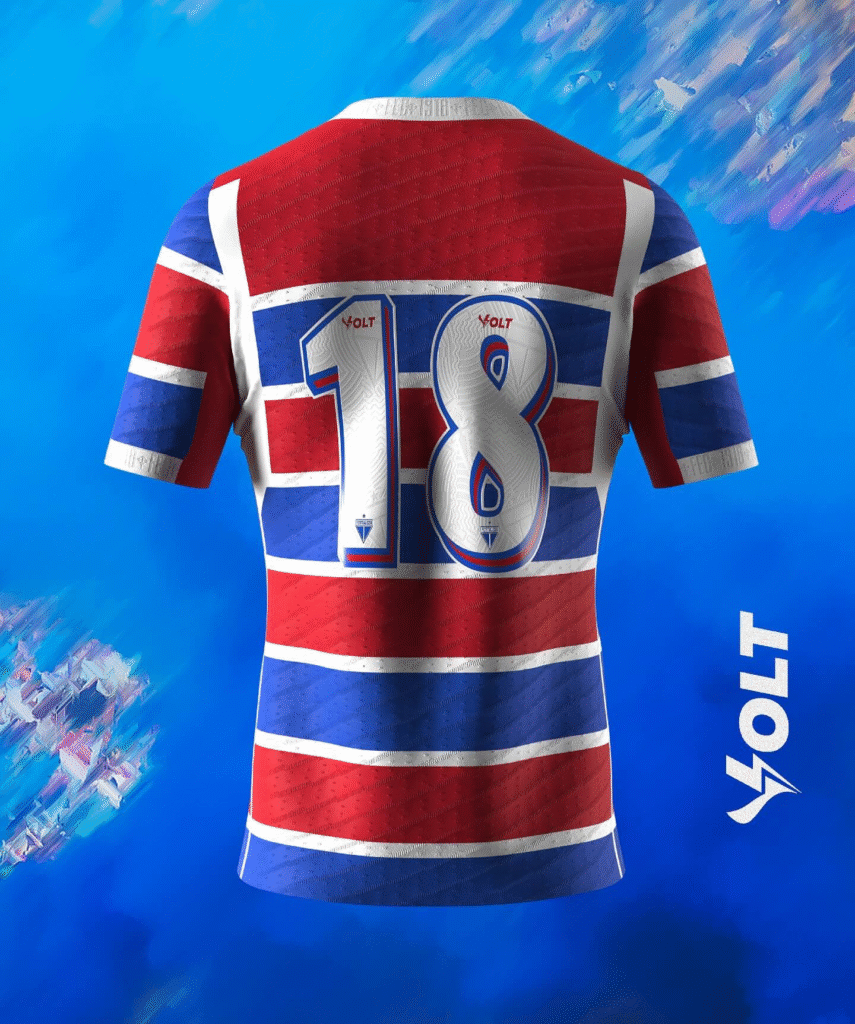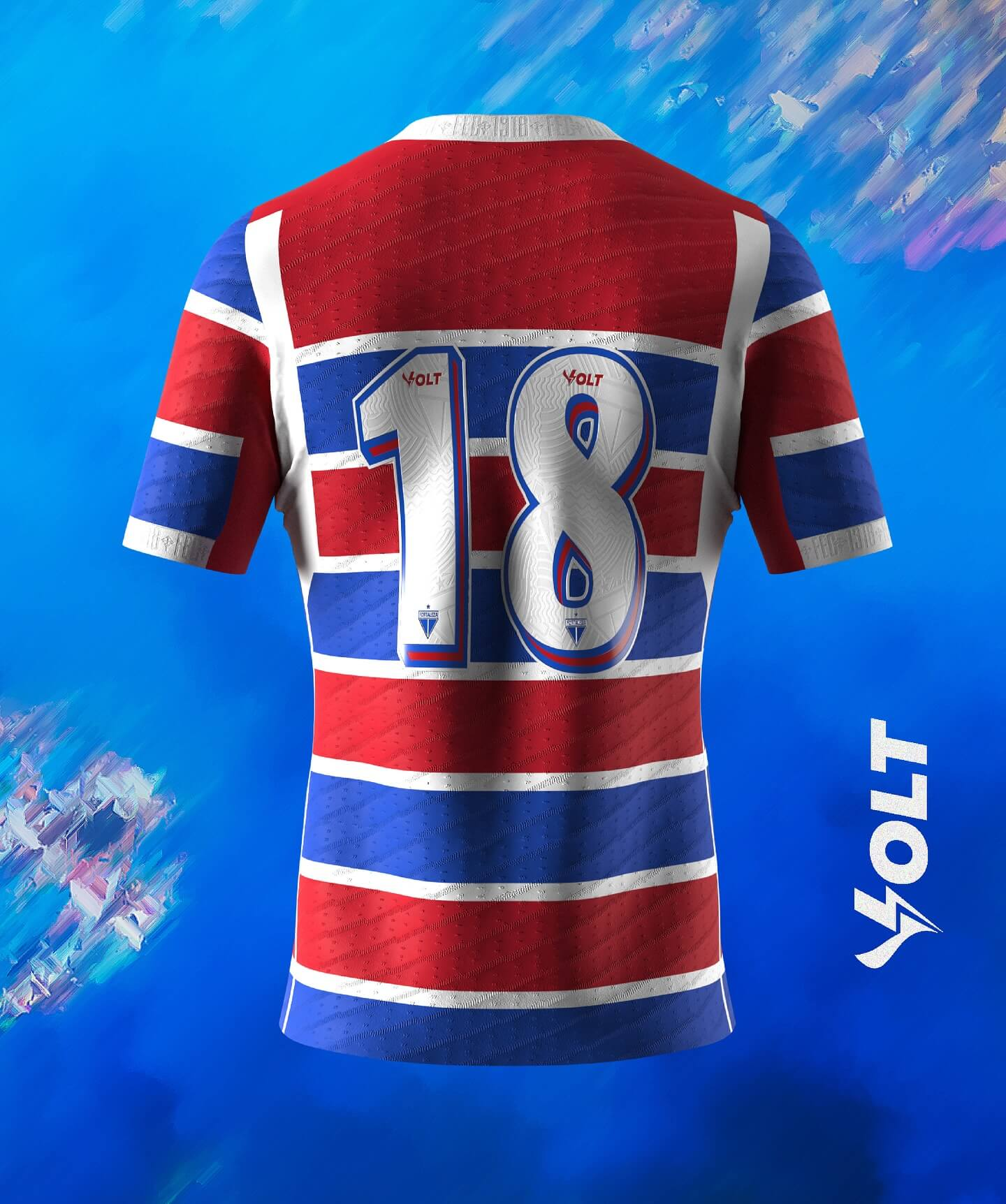
A temporada 2025 do futebol brasileiro mal começou e os uniformes já estão dando o que falar. O Fortaleza Esporte Clube, conhecido por suas camisas vibrantes e cheias de significado, apresentou sua coleção “Gloria”, e a tipografia usada no uniforme visitante (Away) chamou a atenção imediatamente.
O Estilo Visual da “Gloria Font”
A fonte “Gloria” 2025 é moderna e impactante. Ela possui cantos vivos e uma leve inclinação (itálico) que transmite velocidade e dinamismo. Diferente de muitas fontes tradicionais de futebol, ela tem “recortes” estratégicos (vazados) em algumas letras e números, o que a torna instantaneamente reconhecível e agrega um toque de agressividade e elegância. É uma tipografia robusta, com excelente legibilidade em campo, e que reflete perfeitamente o espírito de “Glória e Tradição” do Tricolor de Aço.